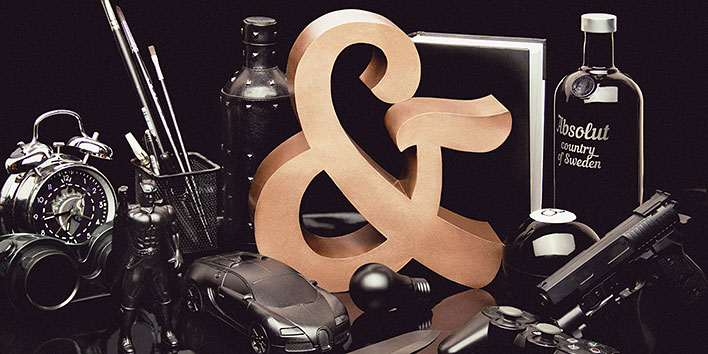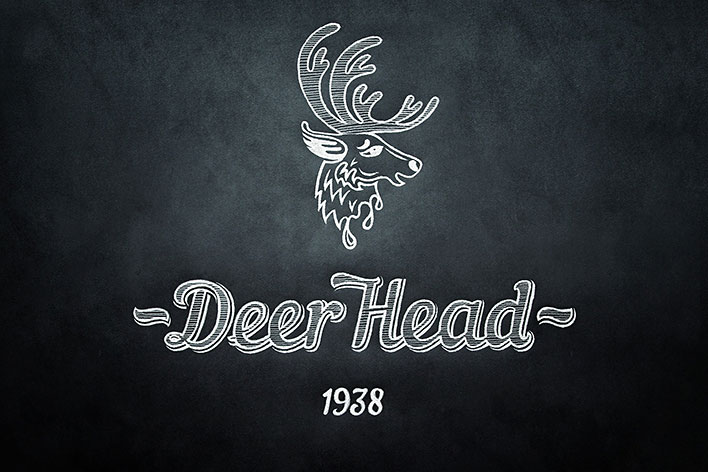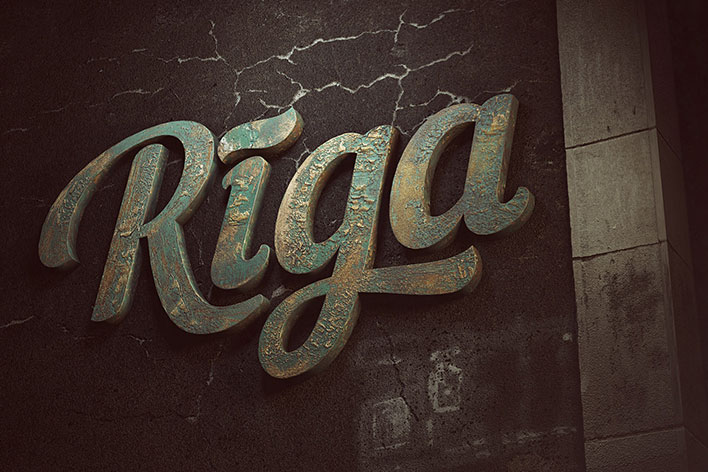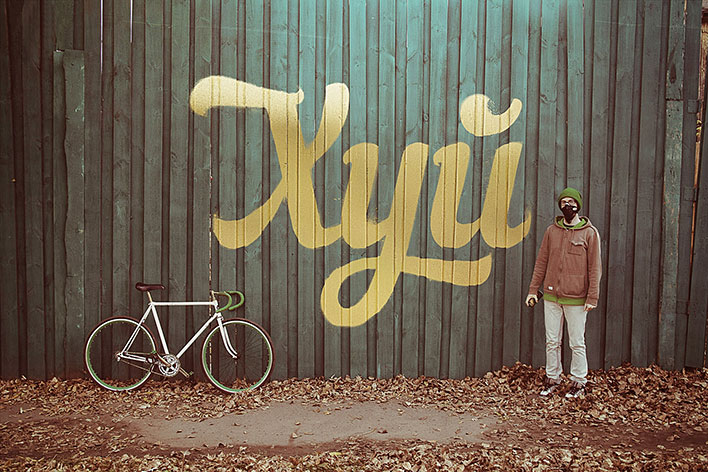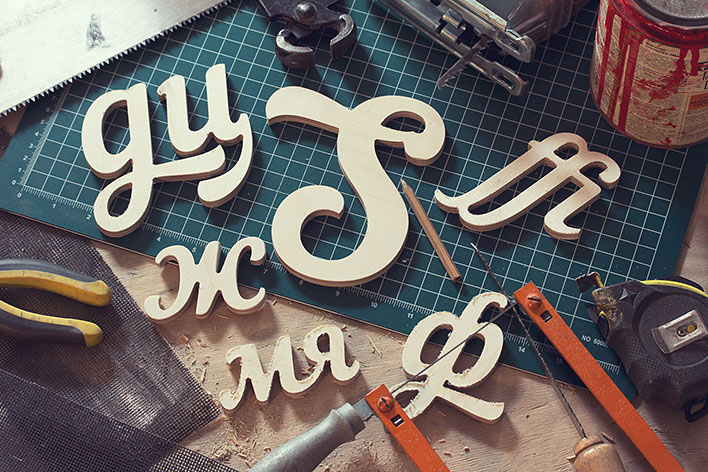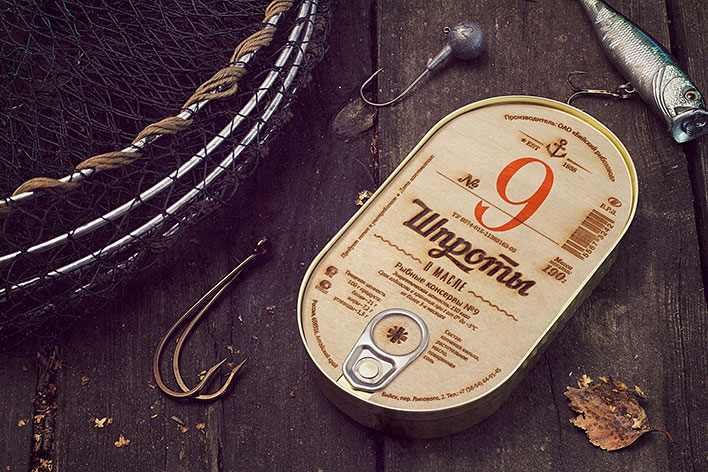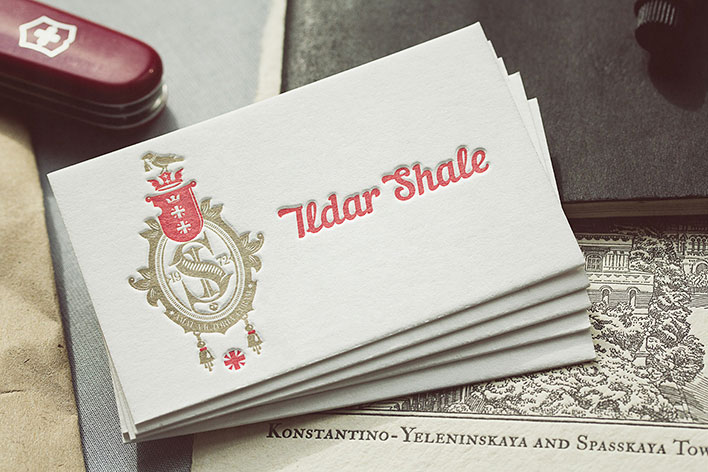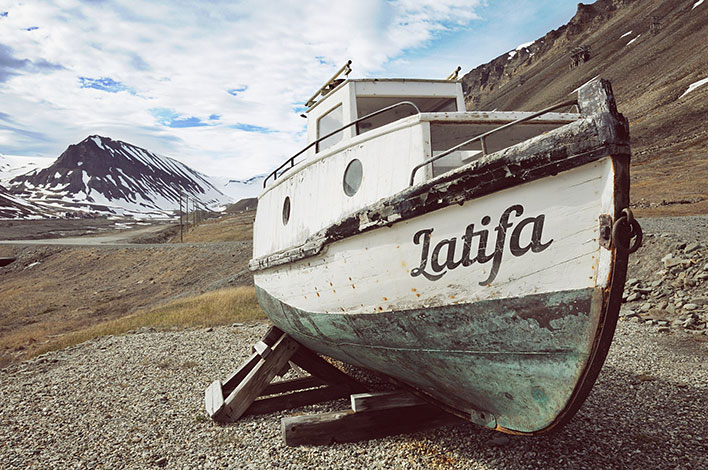
Шрифт Nautilus Pompilius
PUNK YOU BRANDS основано в 2009 году, имеет офисы в Москве и Барнауле. Специализация — создание и продвижение брендов, разработка коммуникационных стратегий и креативных концепций. Через скрупулезный аудит, тщательную аналитику и внимательное изучение текущей ситуации создаются продуманные коммуникации, которые вдыхают жизнь в бренды, помогая им завоёвывать сердца и умы людей. PUNK YOU BRANDS разработали собственный шрифт под названием Nautilus Pompilius. «Наутилус» — это современный скрипт с мягким контрастом. Предназначен для акцидентного набора заголовков, логотипов, афиш. Подробнее ознакомиться с проектом и скачать файл шрифта можно на специальном сайте – nautilustype.